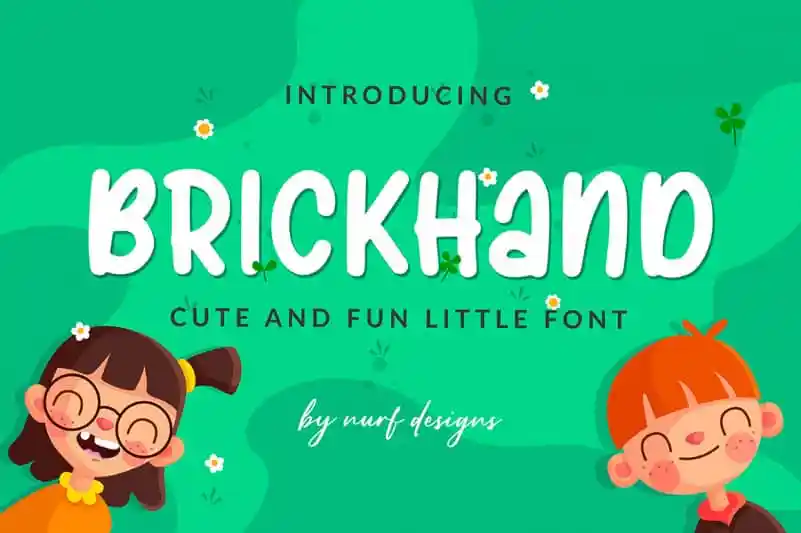
Brickhand Display Font – Download Grátis
A Brickhand Display Font é uma elegante tipografia de exibição que traz alegria para qualquer projeto. Com seu estilo alegre e infantil, esta fonte irá transformar seus projetos de forma impressionante. Suas linhas divertidas, levemente rústicas e encantadoras são ideais para quem busca criar um ambiente criativo e leve em suas produções. Seja para decorar uma página escolar ou qualquer outro projeto destinado a crianças, esta fonte é perfeita para iluminar seu trabalho com uma brisa de diversão e imaginação. Utilize-a para capturar o encanto único das infâncias e deixe que ela transforme suas criações num verdadeiro charme.